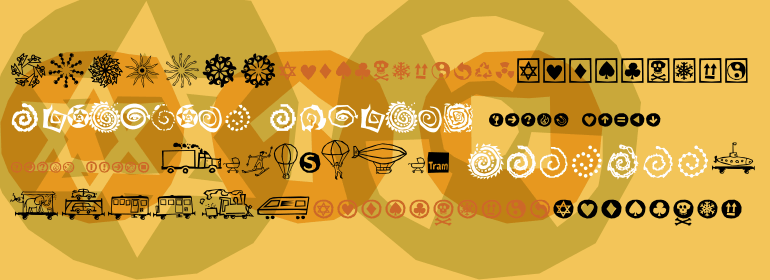
Ale™
Ale™,这款字体结构工整、笔画清晰,兼顾美观与易读性,适用于标题、正文、海报、包装、LOGO 等多种场景。字形优雅稳定,风格百搭耐看,适配日常排版与创意设计,让文字呈现更舒适、更具质感。Ale™一笔一画,皆是细节,以均衡的比例、流畅的线条打造舒适视觉体验,字形端正大气,风格简约现代。无论是商业设计、品牌宣传还是日常排版,都能轻松驾驭,让文字更有格调与力量。Ale™字体下载。